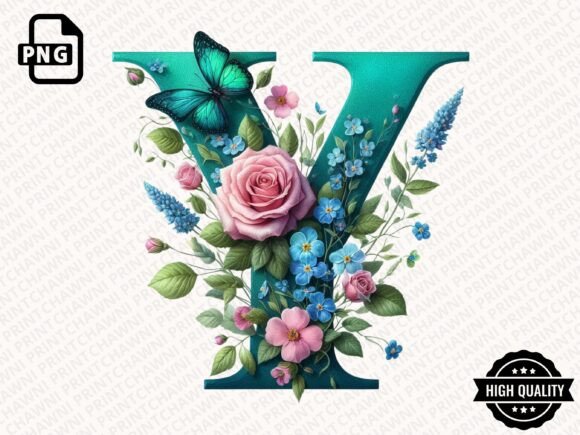
Roses & Butterflies Alphabet Clipart PNG
適切なデザイン要素を見つけるのは難しい場合がありますが、Roses & Butterflies Alphabet Clipart PNGは作品を即座に引き立てる優れたコレクションを提供します。
POD(オンデマンド印刷)製品、結婚式の招待状、またはソーシャルメディアのグラフィックを作成している場合でも、Roses & Butterflies Alphabet Clipart PNGは理想的です。